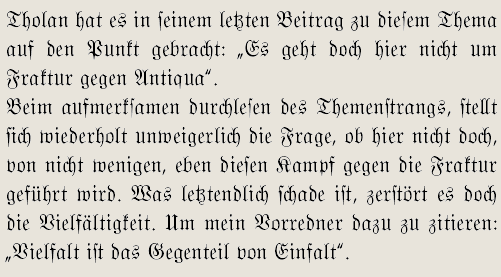
warum sieht die fraktur aus, wie sie aussieht?
Gerade die S-Regeln hilft ihnen, Zusammensetzungen, sonst selbständiger Teilwörter, besser zu erkennen…
Selbst wenn es stimmt, was sagt das schon aus? Die Antiqua hat sich, nicht ohne Grund durchgesetzt, und es gibt daran nichts zu rütteln. Selbst wenn Fraktur marginale Vorteile hätte, will sie heute keinen mehr zurückhaben.
Kennt noch jemand Betamax? Das war VHS auch überlegen und es hat trotzdem nichts genützt. Was die Masse benutzte wurde zum Standard. Der Rest musste abdanken.
Kannst Du bitte konkrete Beispiele nennen?
Ich habe es von bekannten in Nord- und Südamerika erfahren, die Deutsch gelernt haben. Abgesehen davon hab ich dies schon in irgendwelchen gescheiten Studien/Bücher gelesen, aber du überforderst mich, wenn du mich jetzt fragst in welchen … so was vergesse ich immer wieder.
(Vielleicht sollte ich dazu noch erwähnen, daß es Nord- und Südamerika deutschsprachige Siedlungen gibt, wo die gebrochene Schrift noch ihren Platz hat. Und daher die Umwelt eher mit der gebrochenen Schrift in Berührung kommt den in Deutschland.)
Gerade die S-Regeln hilft ihnen, Zusammensetzungen, sonst selbständiger Teilwörter, besser zu erkennen…
Selbst wenn es stimmt, was sagt das schon aus? Die Antiqua hat sich, nicht ohne Grund durchgesetzt, und es gibt daran nichts zu rütteln. Selbst wenn Fraktur marginale Vorteile hätte, will sie heute keinen mehr zurückhaben.
Der Grund liegt wohl eher an den beschränkten Schreibmaschinen und später der Computer Tastaturen und nicht zuletzt an dem Diktat von 1941.
Der Grund liegt für mich noch eher darin, dass eine Schrift für alle (und das bedeutet heute international) funktionieren muss. Warum zurück in die schriftliche Isolation? Fraktur ist schön und muss nach ihren eigene Regeln gesetzt werden, keine Frage. Aber sie bleibt in der Realität des 21. Jahrhunderts Liebhaberei. Wie Slow Food und Plattdeutsch. Dafür gibt es auch lobenswerte Vereine (ich mag alle drei: Fraktur, Slow Food und Platt), aber es ist, wenn man es zynisch sagen will, "Kulturzoo".
... ich kann dir meine eigene wissenschaftliche untersuchung zur verfügung stellen. bei uns gibt es hier einen türkisches 'bistro' das verkauft:
»JÄGERMEIFTER«soviel dazu.
das sagt gar nichts, weil da gibt es auch genügend Antiqua-Beispiele in haarsträubende Schreibweise.
Und da muss man nicht lange suchen.
... Selbst wenn Fraktur marginale Vorteile hätte, will sie heute keinen mehr zurückhaben ...
ich verstehe, was Du meinst, aber es geht doch hier nicht um Fraktur gegen Antiqua.
Und wenn man das lange-s und die Ligaturen mag, warum nicht!
... ich kann dir meine eigene wissenschaftliche untersuchung zur verfügung stellen. bei uns gibt es hier einen türkisches 'bistro' das verkauft:
»JÄGERMEIFTER«soviel dazu.
das sagt gar nichts, weil da gibt es auch genügend Antiqua-Beispiele in haarsträubende Schreibweise.
Und da muss man nicht lange suchen.
wie das sagt gar nicht? mir sagt das, dass das lange-ß unseren ausländischen
mitbürgern wohl eher nix sagt, bzw. diese das mit einem f verwechseln. ich
habe sowas schon oft gesehen.
mir sagen viele internationale Buchstaben und deren Eigenheiten von vornherein auch nichts.
Auch im Türkischen gibt es da wohl ein paar Abwandlungen des lateinischen Alphabets,
obwohl es ganz jung ist.
Türkçe, Türkiye Elektrik Dağtım A.Ş (Türkische Stromverteilungs AG) hätte ich vielleicht auch falsch geschrieben,
wenn’s mich nicht interessiert hätte.
Übrigens hier auch ganz sinnige Schriftumsetzungen für Eigenheiten der Sprache.
ç=tsch
Ş für Sch
http://www.spiegel.de/kultur/zwiebelfis ... 52,00.html
0,1020,728037,00.jpg
eingeschickt von Doris Fröhlich, Darmstadt-Eberstadt
Gefunden bei Antalya in der Türkei.
Ich habe als Kind die Bücher meines Vaters (Mutters Bücher sind zerbombt worden) gelesen und im Robinson Crusoe mit den lang-s gekämpft. Erbfen gibt es zwar nicht, aber Robinfon Cruefoe (á la Daniel Defoe) könnte es ja geben....
Ich lese gerne Fraktur, da spielt Nostalgie eine Rolle. Für eine echte Renaissance in Alltagstexten sehe ich allerdings auch keine Chance. Kulturzoo? Gerne. Vielfalt ist das Gegenteil von Einfalt, variatio delectat, als Westfale liebe ich Töttchen, Potthast oder Buchweizenpfannkuchen. Nicht jeden Tag, wohl verstanden.
Aber genau so, wie ungekonntes Plattdeutsch peinlich ist, sollte auch Fraktur korrekt gesetzt sein, wenn schon. In der Schule sollte man es lernen können, Profis im Schriftgeschäft sollten es wissen müssen, weil gute Ideen dahinterstecken, funktionale, ästhetische, stilistische, historische, kulturelle...
Daß in unseren Schulen wichtigere Sachen nicht gelehrt werden, ist bitter, aber das Lehren der Fraktur würde den Schülern den direkten Zugang zu älteren Druckwerken erleichtern und eine Hürde zur Bildung abbauen.
denken. denn es ist ja eindeutig das die fraktur wieder im kommen ist.
wenn auch nur im displaybereich. für mich reicht das, als textschrift will
ich eine schwabacher heute nicht mehr lesen müssen. es sei denn sie ist
so abstrahiert das sie mir das lesen nicht erschwert.
die frage ist, ob man sie auch so nutzen soll/will. für den internationalen
sprachgebrauch würde ich auf das lange-s verzichten, dazu sollte man
offen und nicht verbohrt an diese schriften herangehen, ich glaube ich
wiederhole mich ...